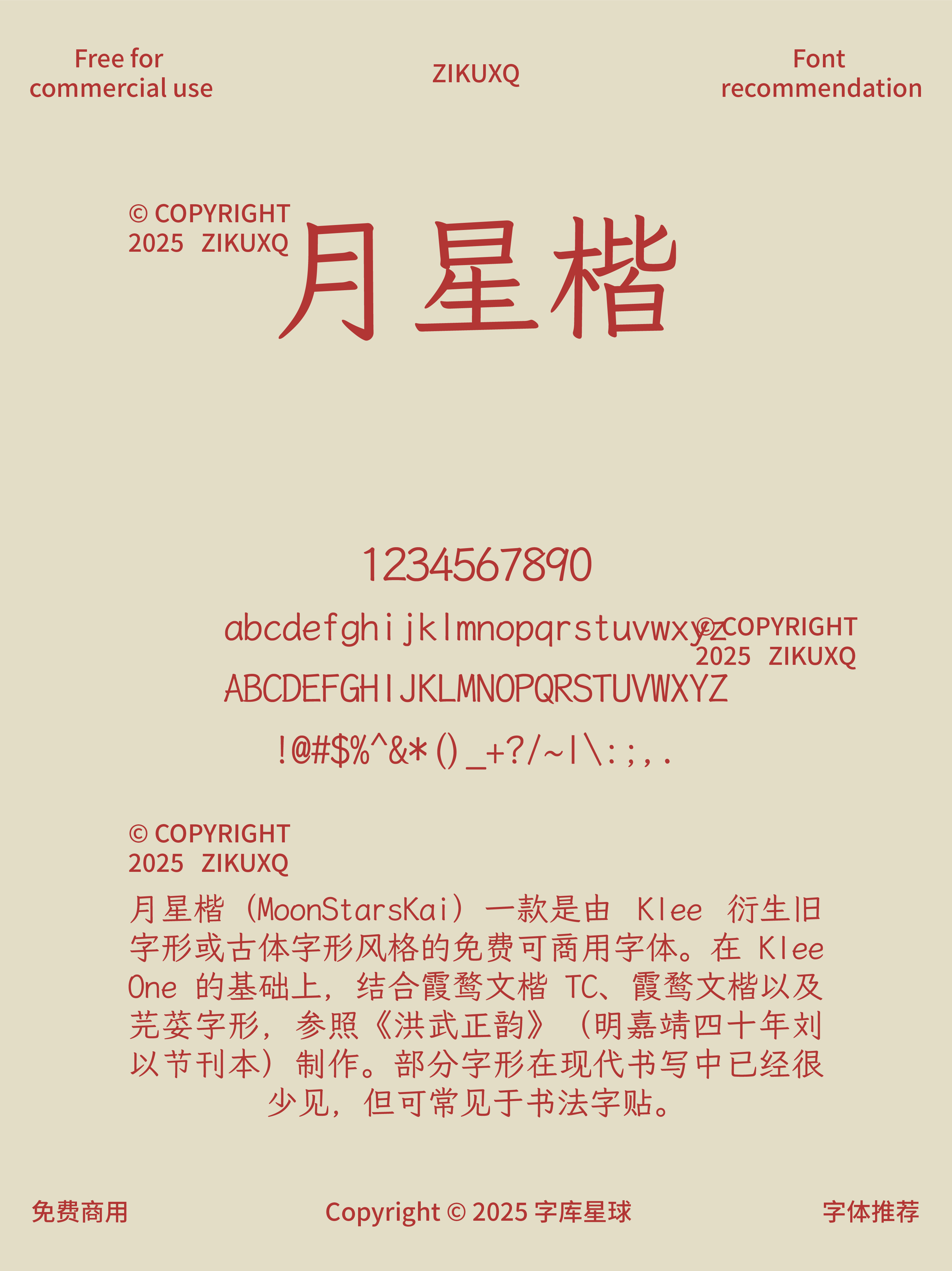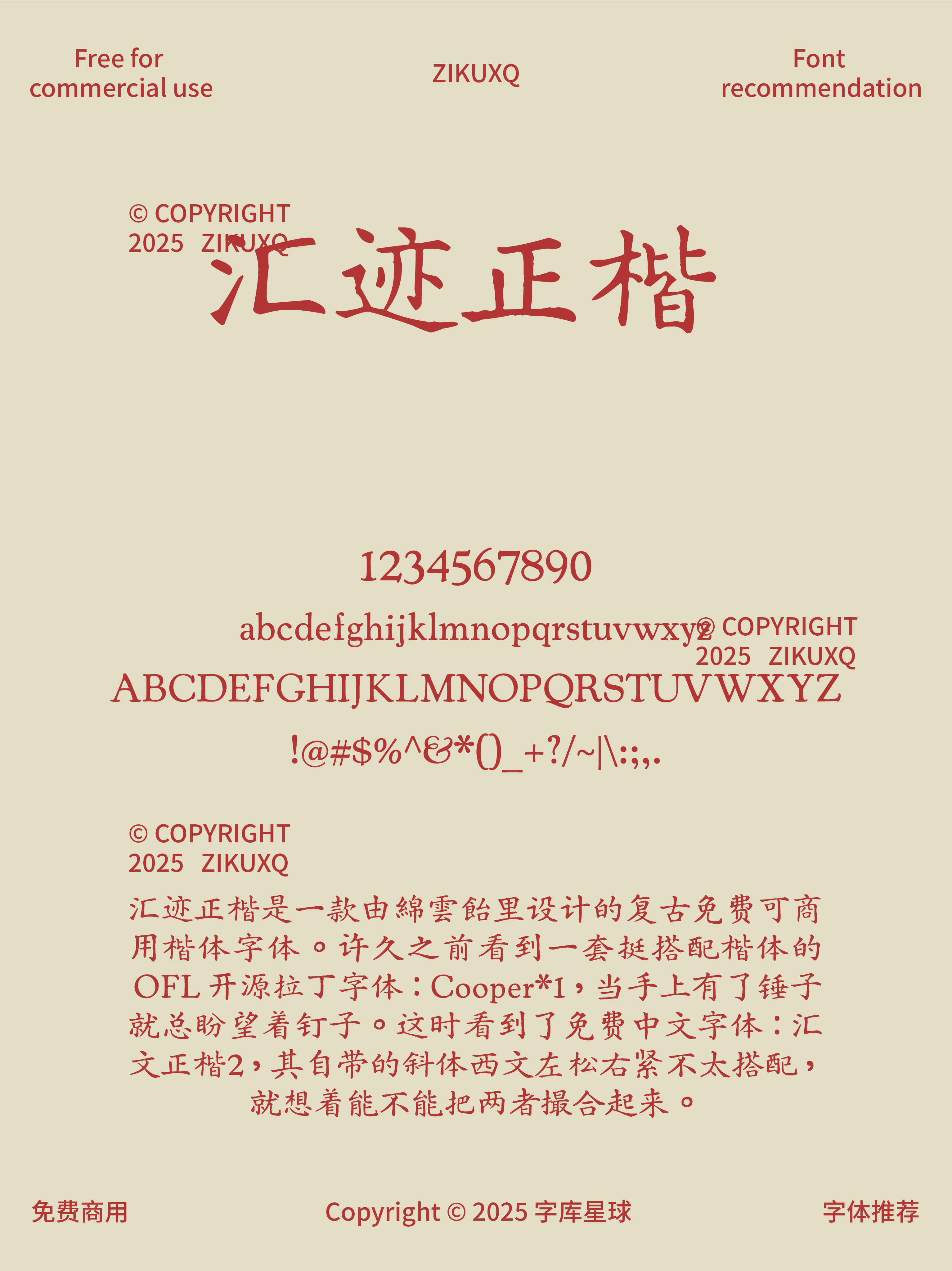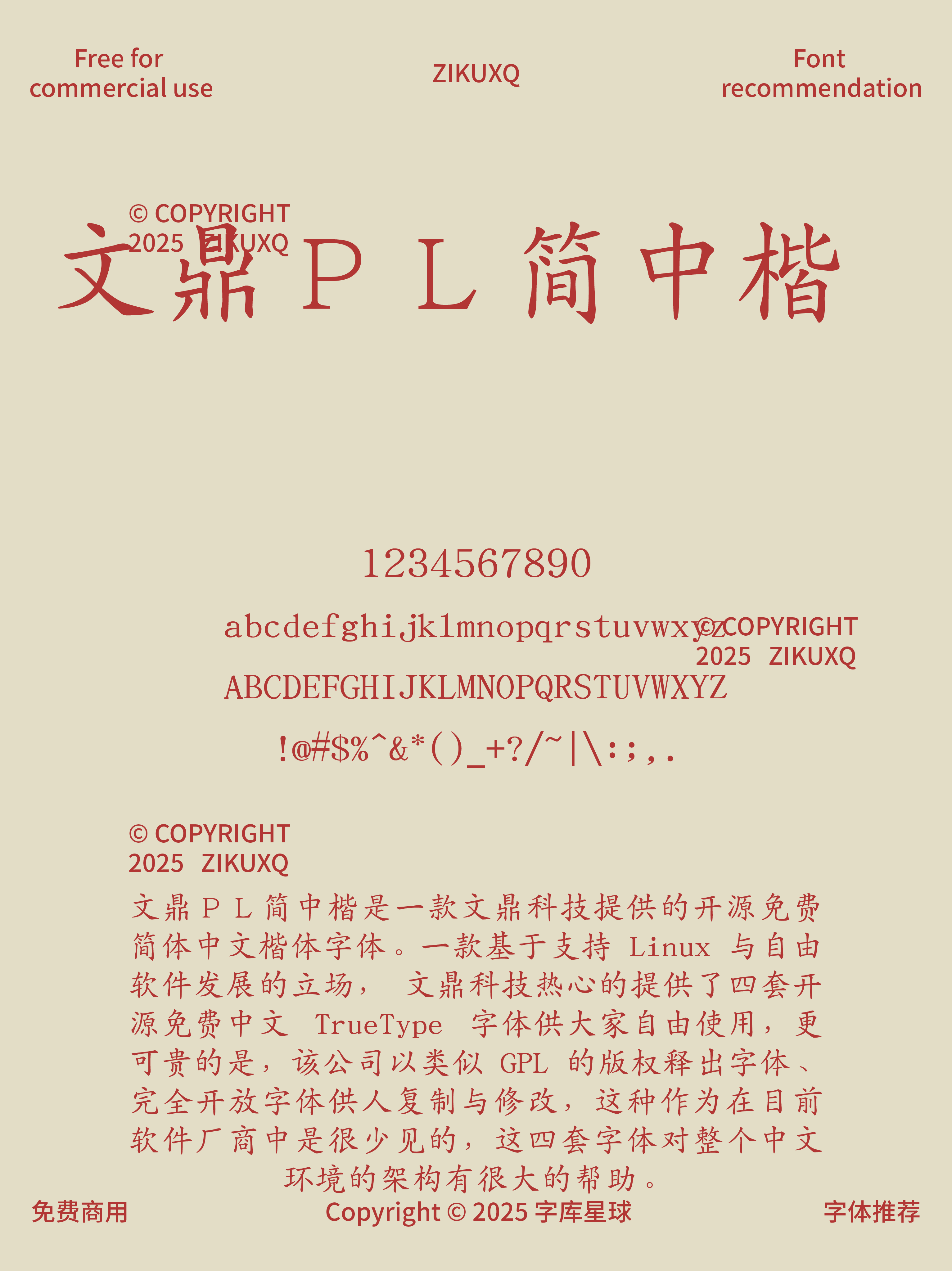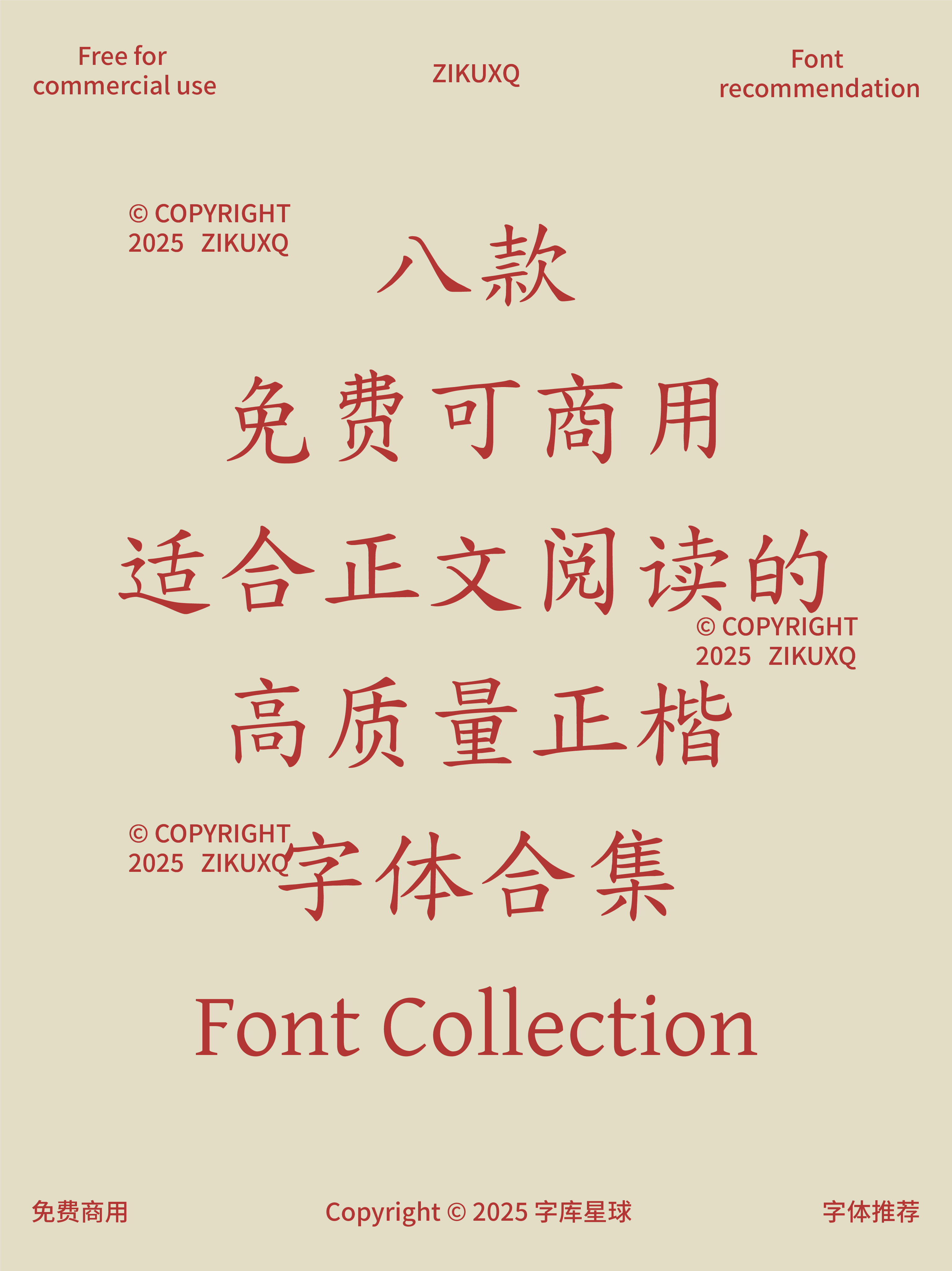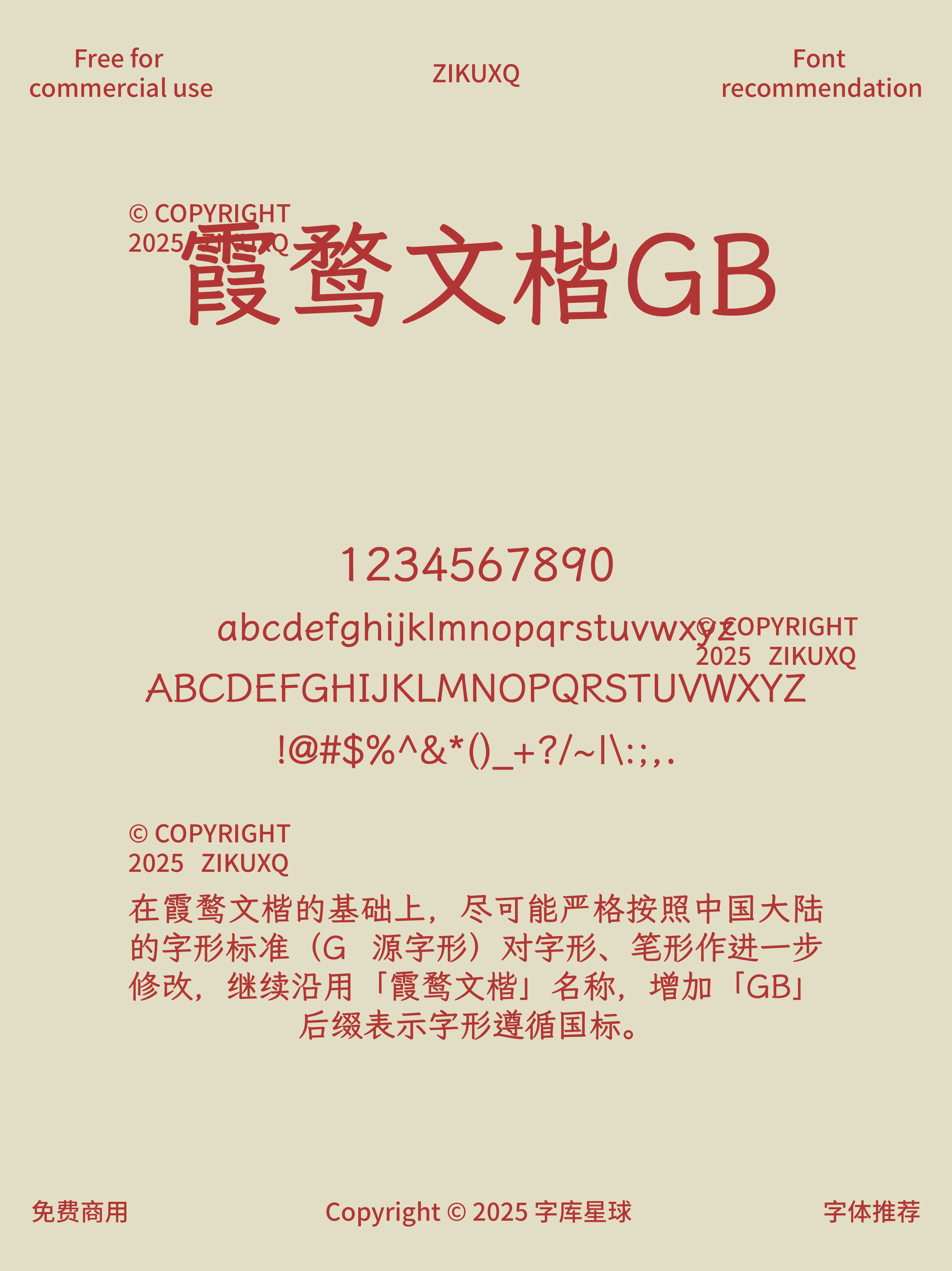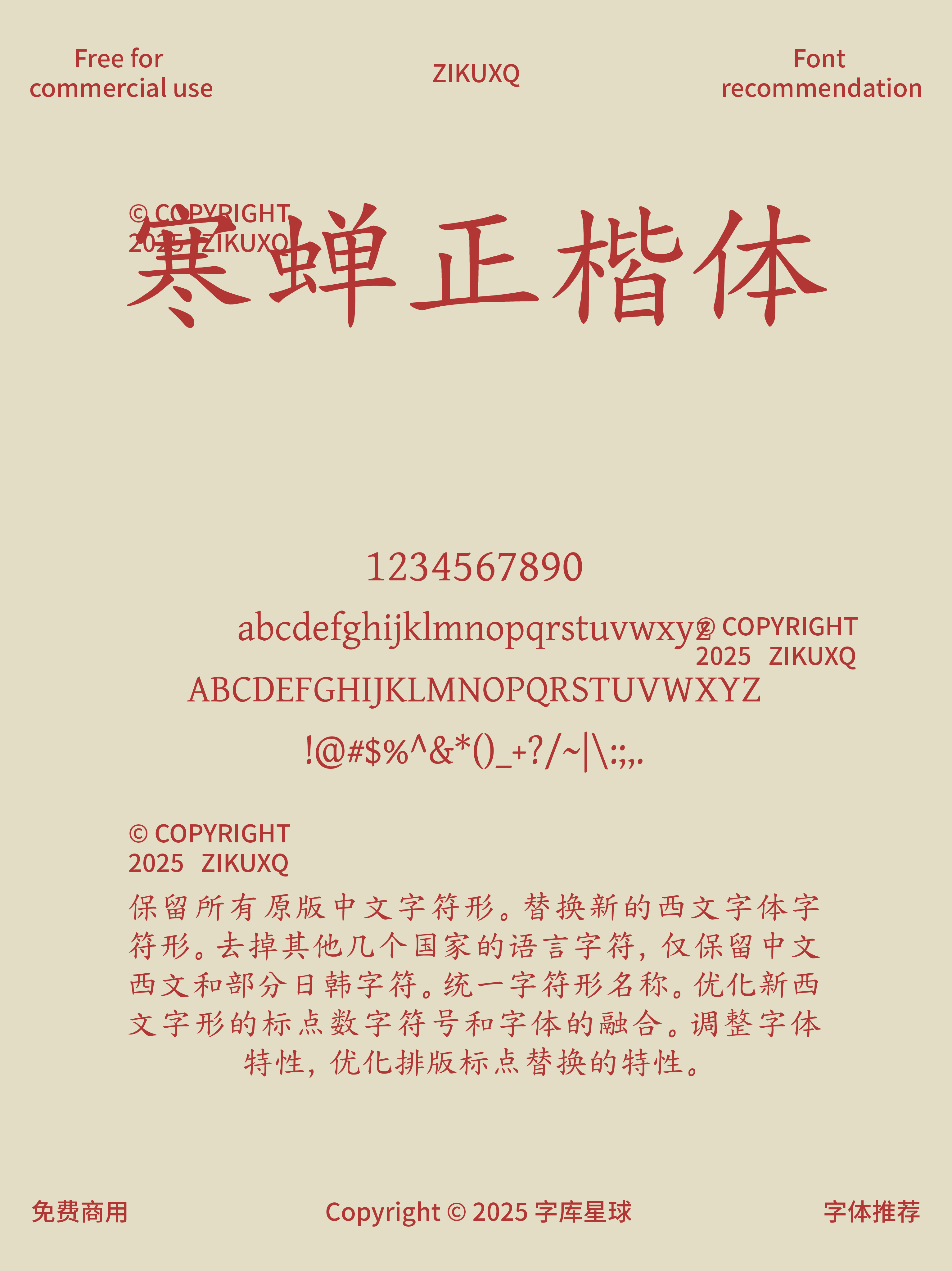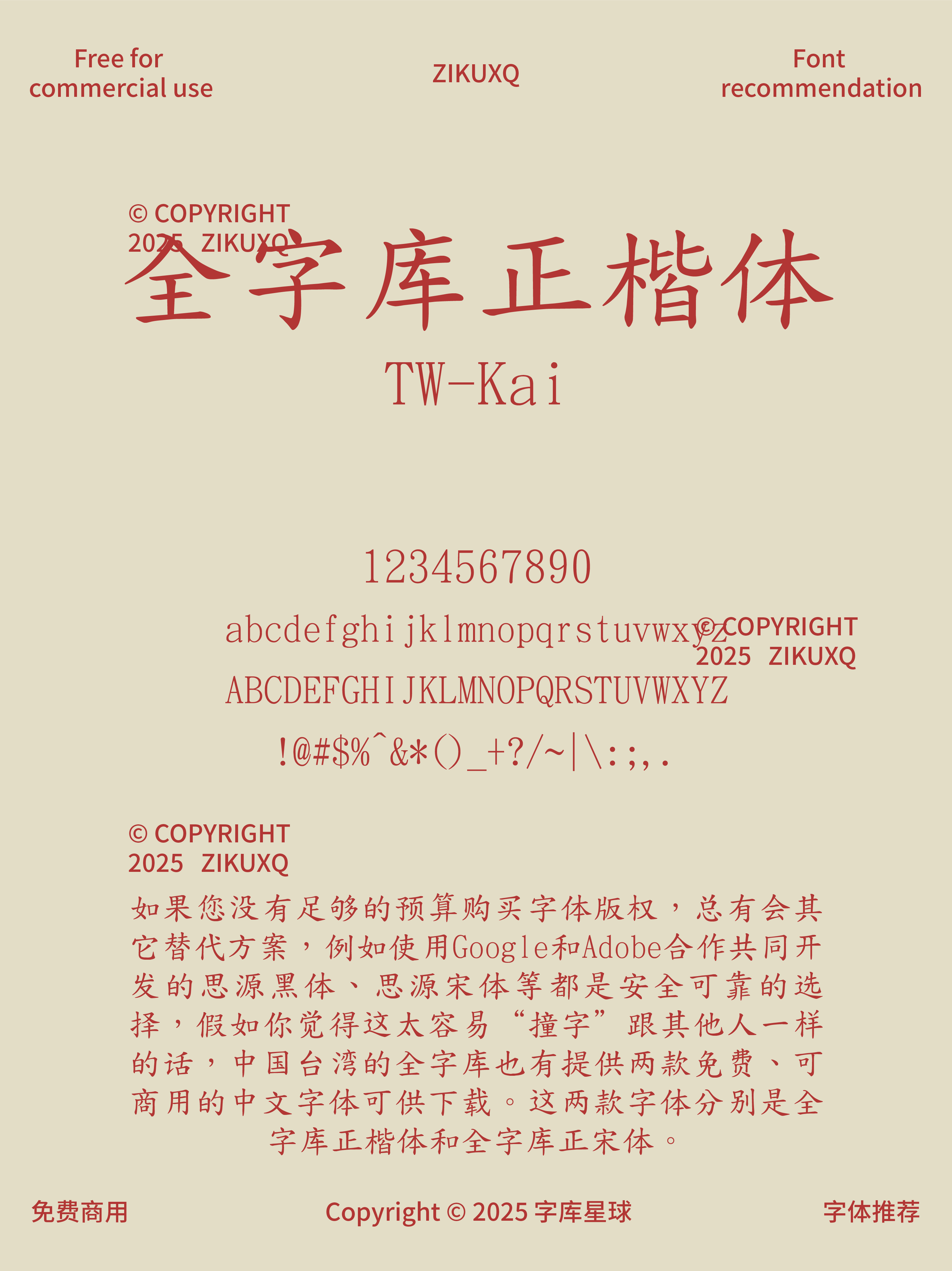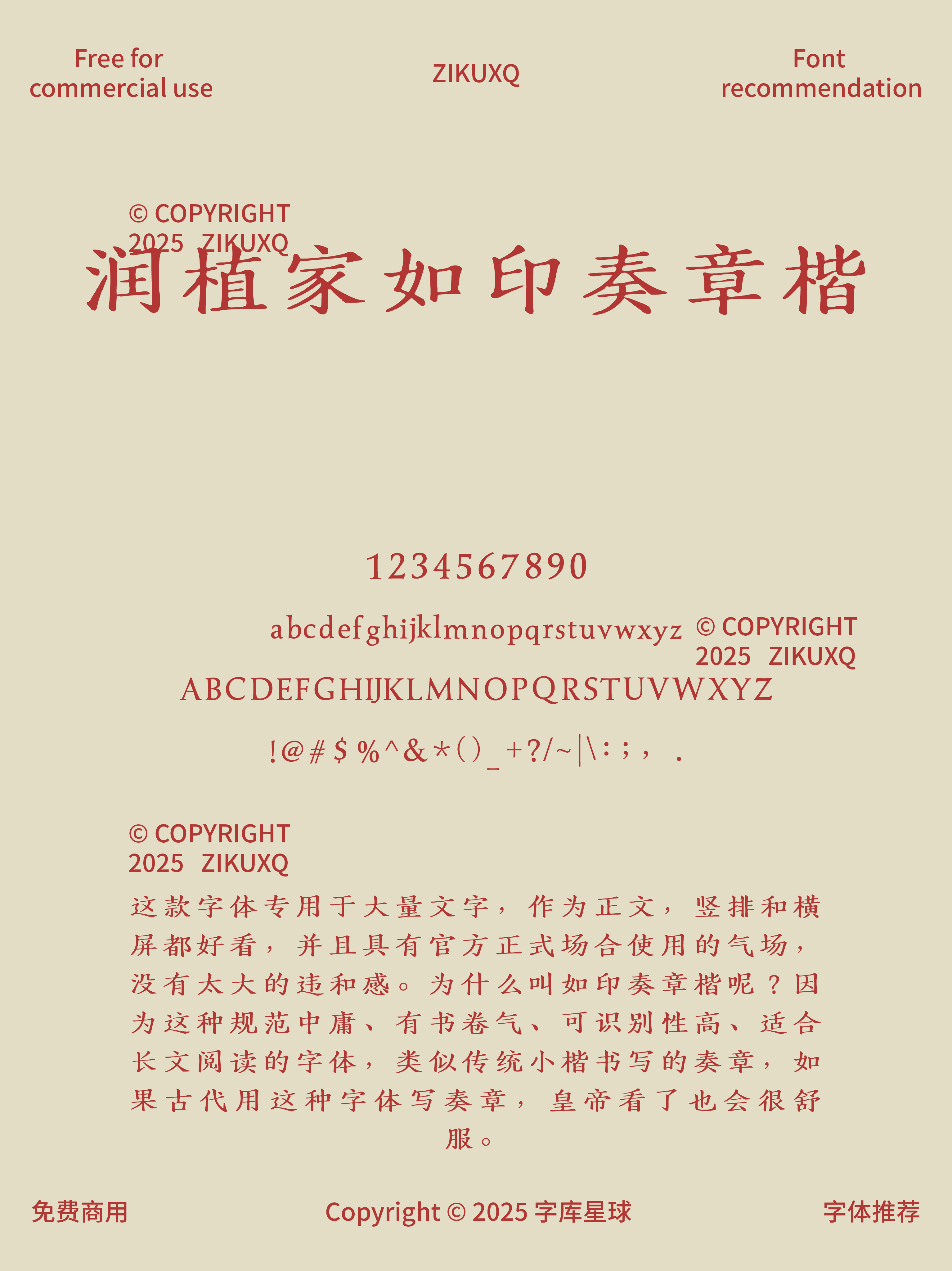
八款免费可商用适合正文阅读的高质量正楷字体
这几款字体对简体和繁体都有很好的支持,虽然简体字形略有差异,但却有着独特的韵味。字体笔画清晰,结构严谨,呈现出传统正楷的端庄大气,用于正文,不仅易读,还能增添一份文化底蕴。
兼具仿宋和楷体的特点,可读性超高。它拥有简繁日韩均支持的多种字重,字形优美,笔画粗细适中,在正文排版中,能给人一种清新雅致的感觉,长时间阅读也不会觉得累眼,强烈推荐!